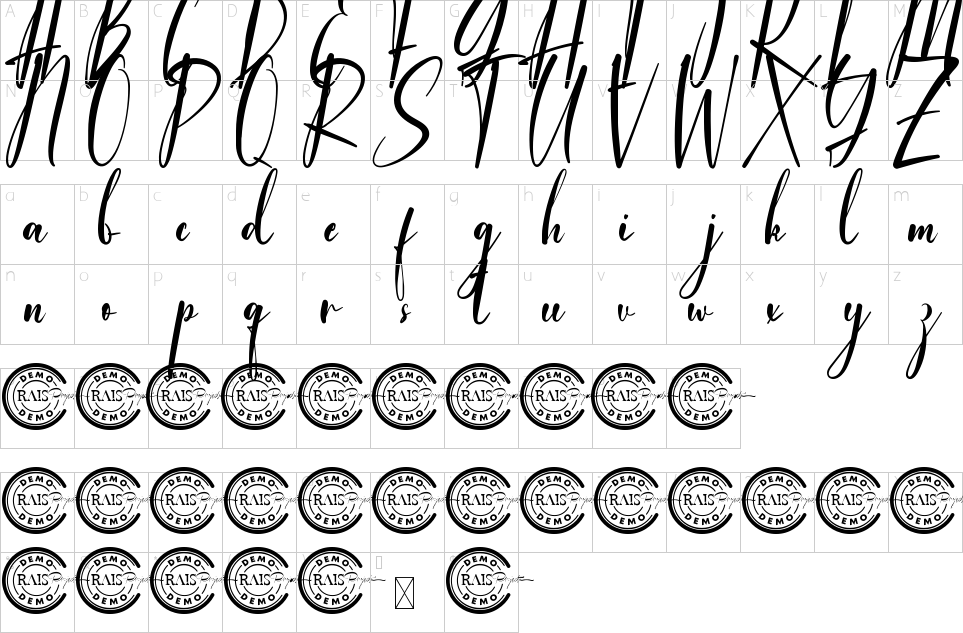
Descubra a tranquilidade e a sofisticação que uma fonte de nome Arabica Chocolate pode trazer a seus projetos. Esta fonte foi projetada por RaisProject e é uma verdadeira paixão para os olhos, com seus traços finos e suaves. Com uma categoria dedicada a fontes gratuitas, esta font está disponível tanto para usuários de Windows quanto para Mac, possibilitando a você a diversidade de escolher a melhor opção para seu projeto. Com mais de mil fontes baixadas, a Arabica Chocolate é um nome a ser apreciado e testado por qualquer designer em busca de um visual elegante e harmonioso. Seja para letramento de logotipos, criação de sites, ou qualquer projeto de design que exigir um toque delicado e sofisticado, esta font será uma escolha inteligente. Descubra agora a delícia de adicionar a sua coleção de fontes a esta encantadora fonte.